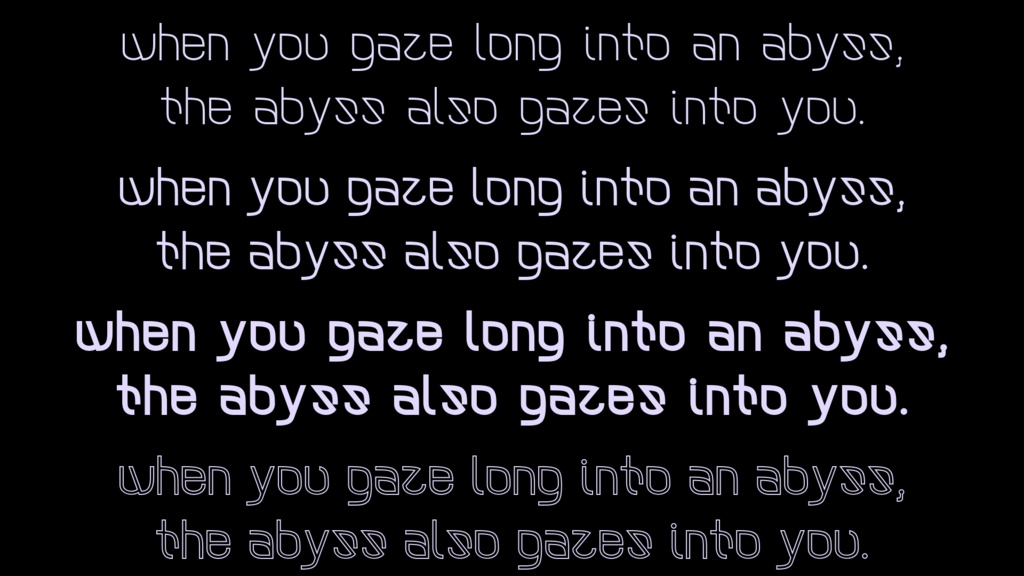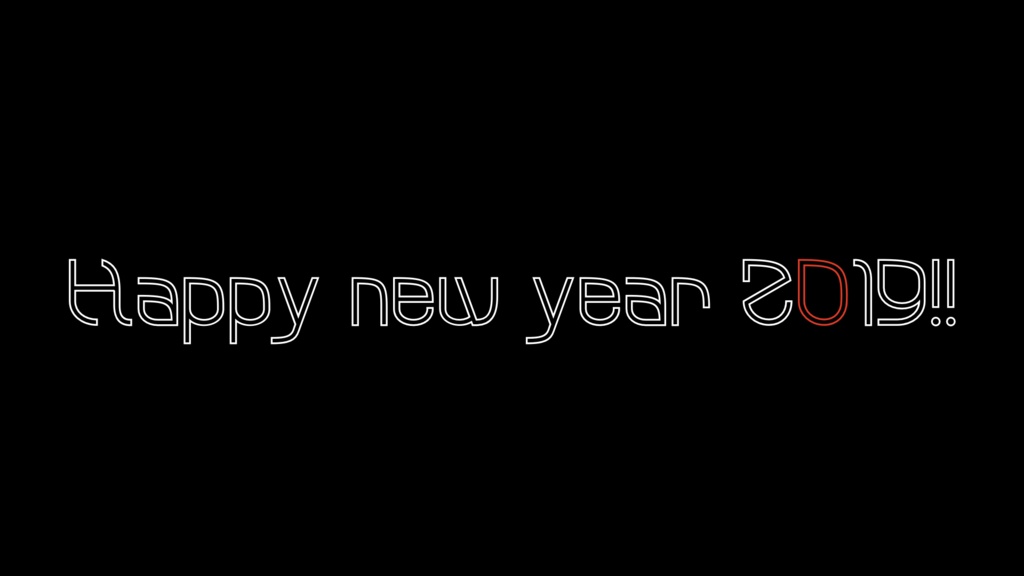
欧文フォント Lemonin (有償完全版)
スタイリッシュだけどどこか可愛い欧文フォントのLemoninです。レモンのような形状がポイント。文章にオシャレなアクセントをつけましょう。 有償完全版ではRegular、Light、Bold、Borderedの4つを一挙収録。ぜひぜひご利用ください。 LINE絵文字でのご利用は制限付きでのみ行えます。 Regularのみの無償版は以下です。 https://fontring.booth.pm/items/1156964 フォントのバージョンアップのお知らせはこちらで投稿します。フォローお願いします🙏 https://www.pixiv.net/fanbox/creator/31276656